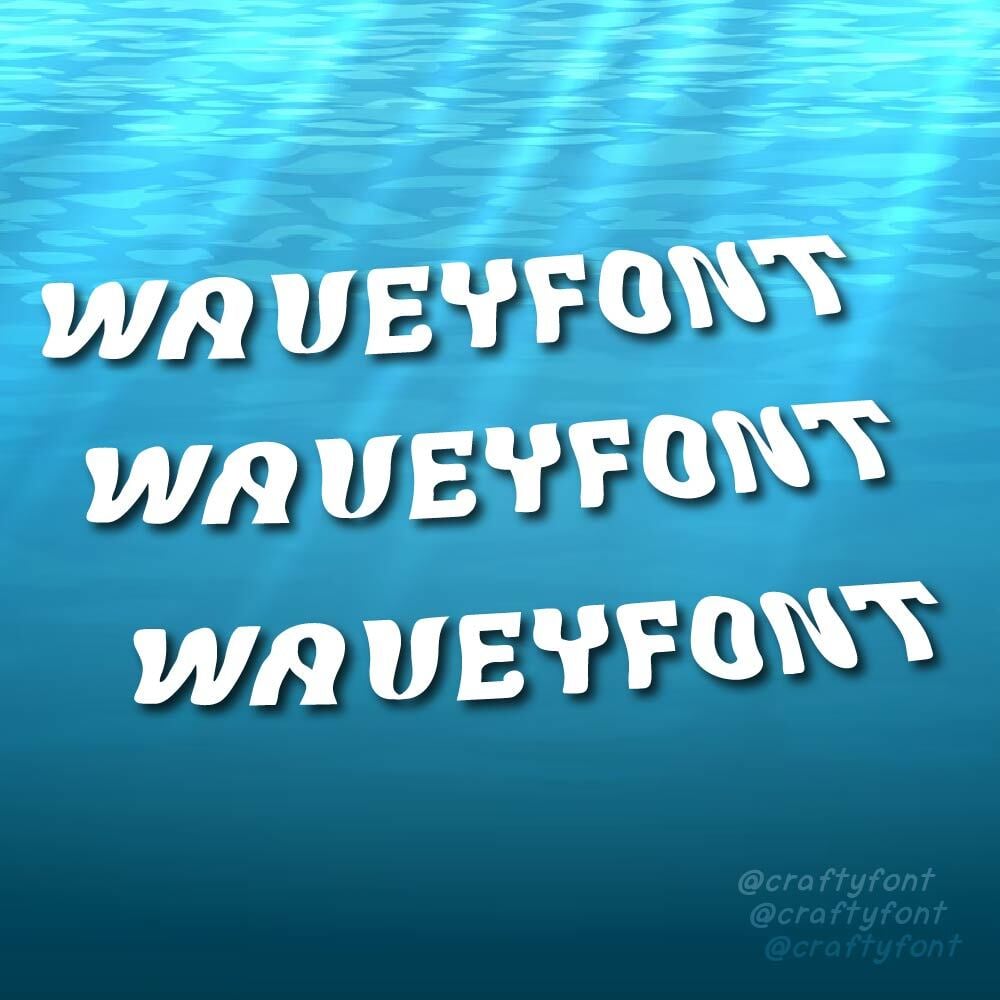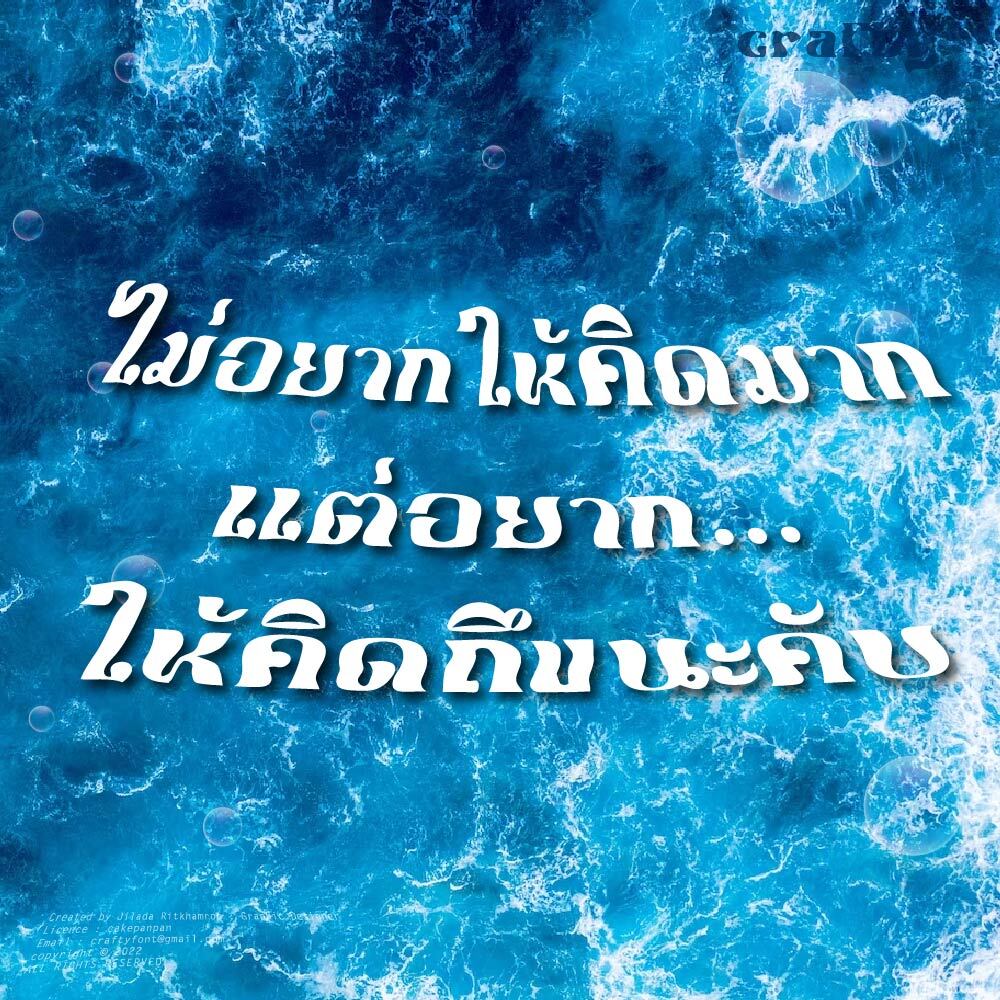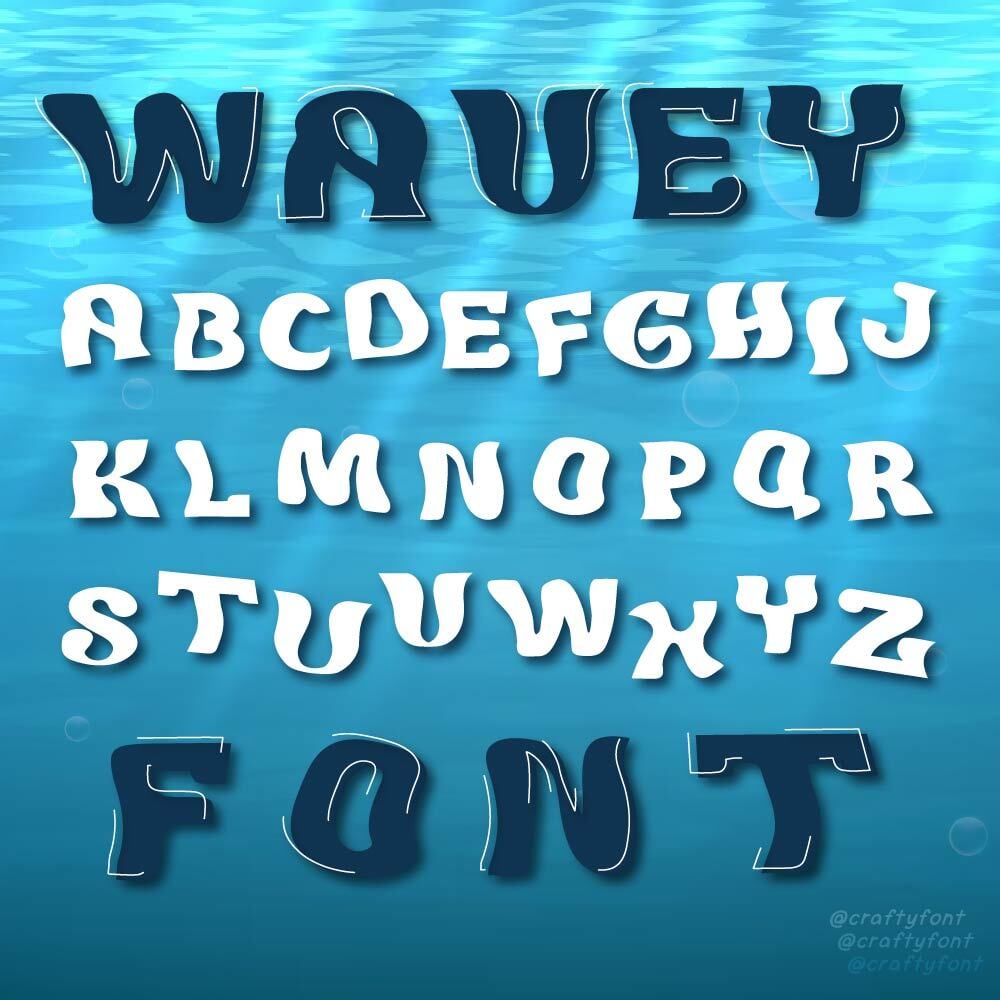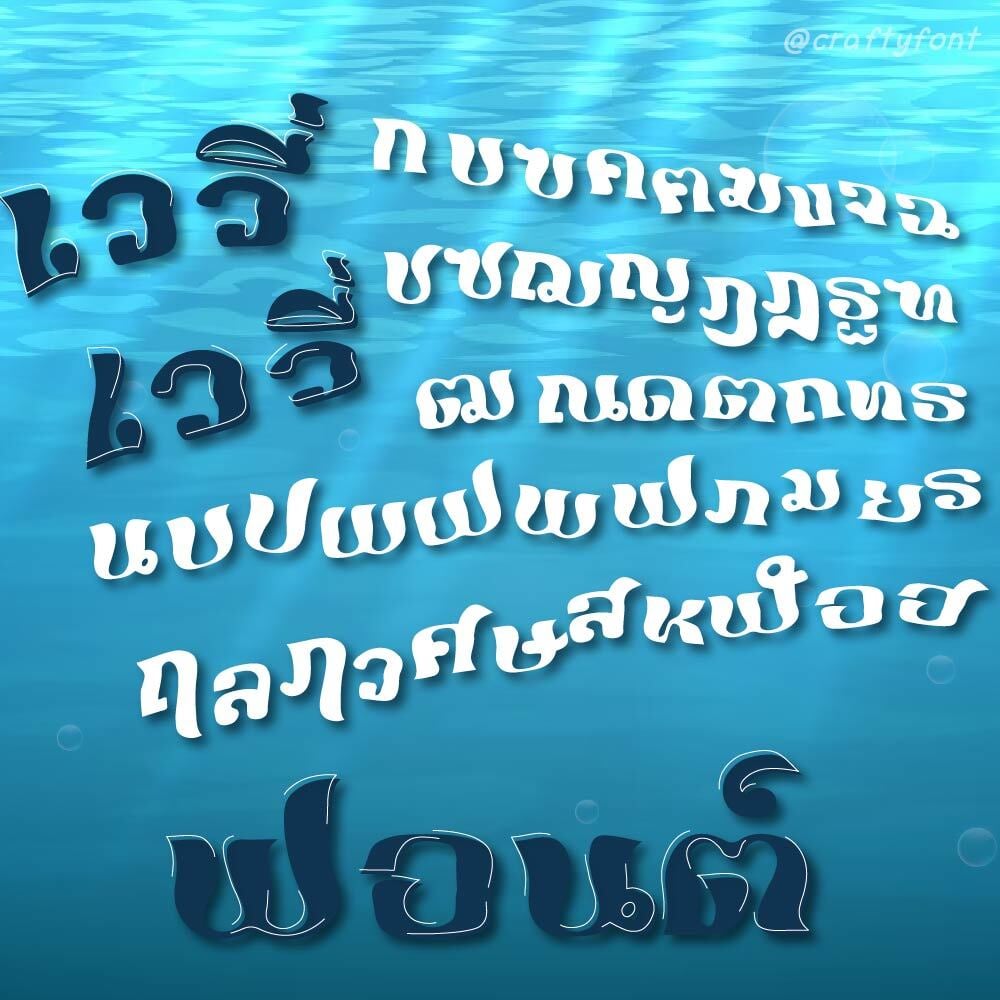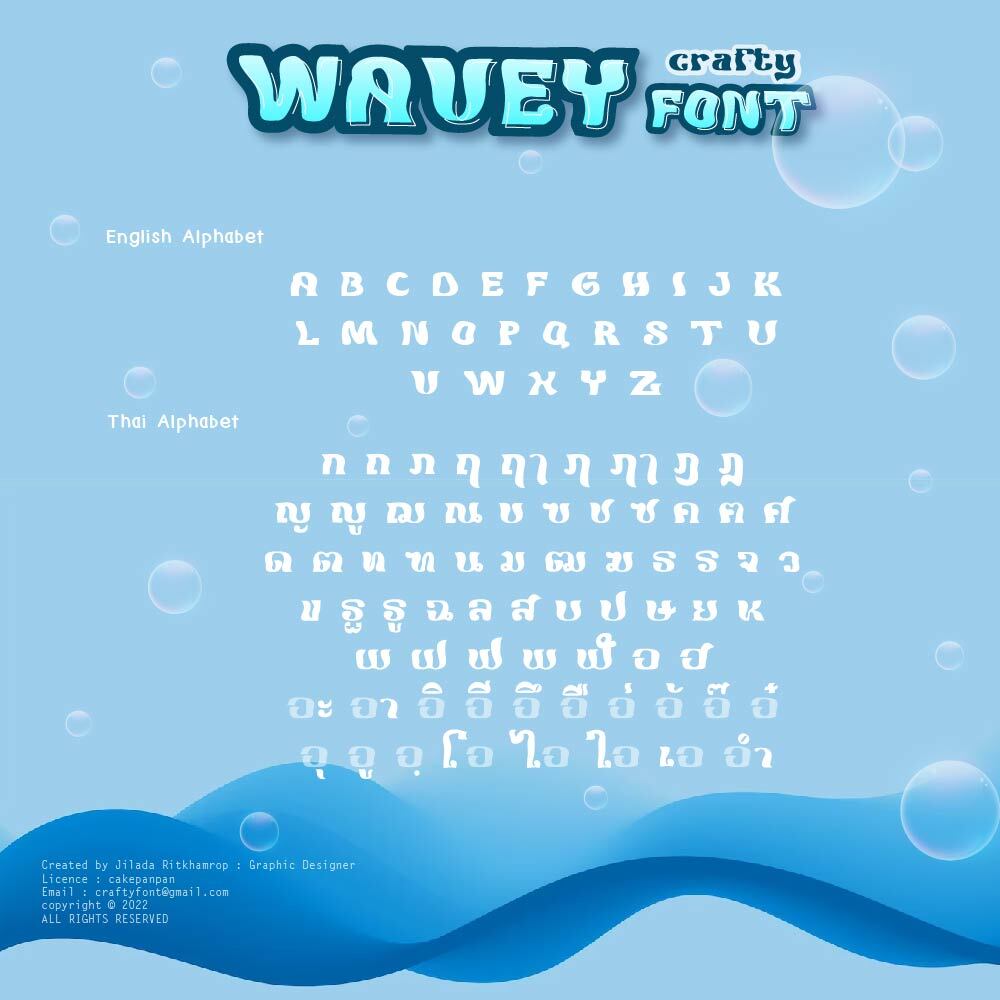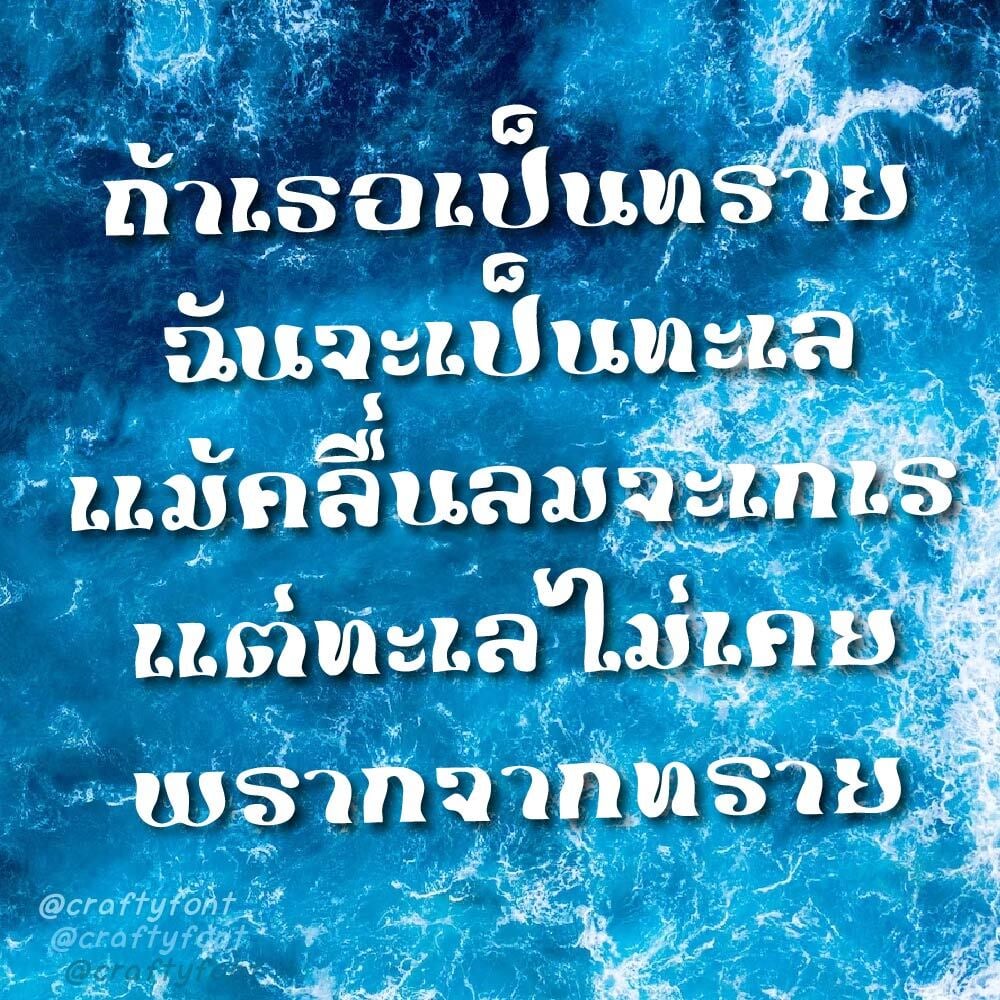
Wavey Font (ฟอนต์เววี่)
ฟอนต์พลังคลื่นนนนน น้องตัวอวบอ้วน ตัวใหญ่มากจากที่เคยทำมามากเลย เหมาะแก่การพาดหัวมาก อ่านง่าย ดีไซน์ให้ตัวยึกยือไปมาเหมือนคลื่นทะเล
เหมาะกับการทำภาพสวัสดีวันจันทร์ส่งตามไลน์กลุ่ม สว. สูงวัย  😗
ฟอนต์เววี่มีตัวปกติ และตัวเอียง พิมพ์ได้ทั้งภาษาไทยและภาษาอังกฤษเลย สัญลักษณ์บวกลบคูณหารมีให้พร้อมใช้งาน